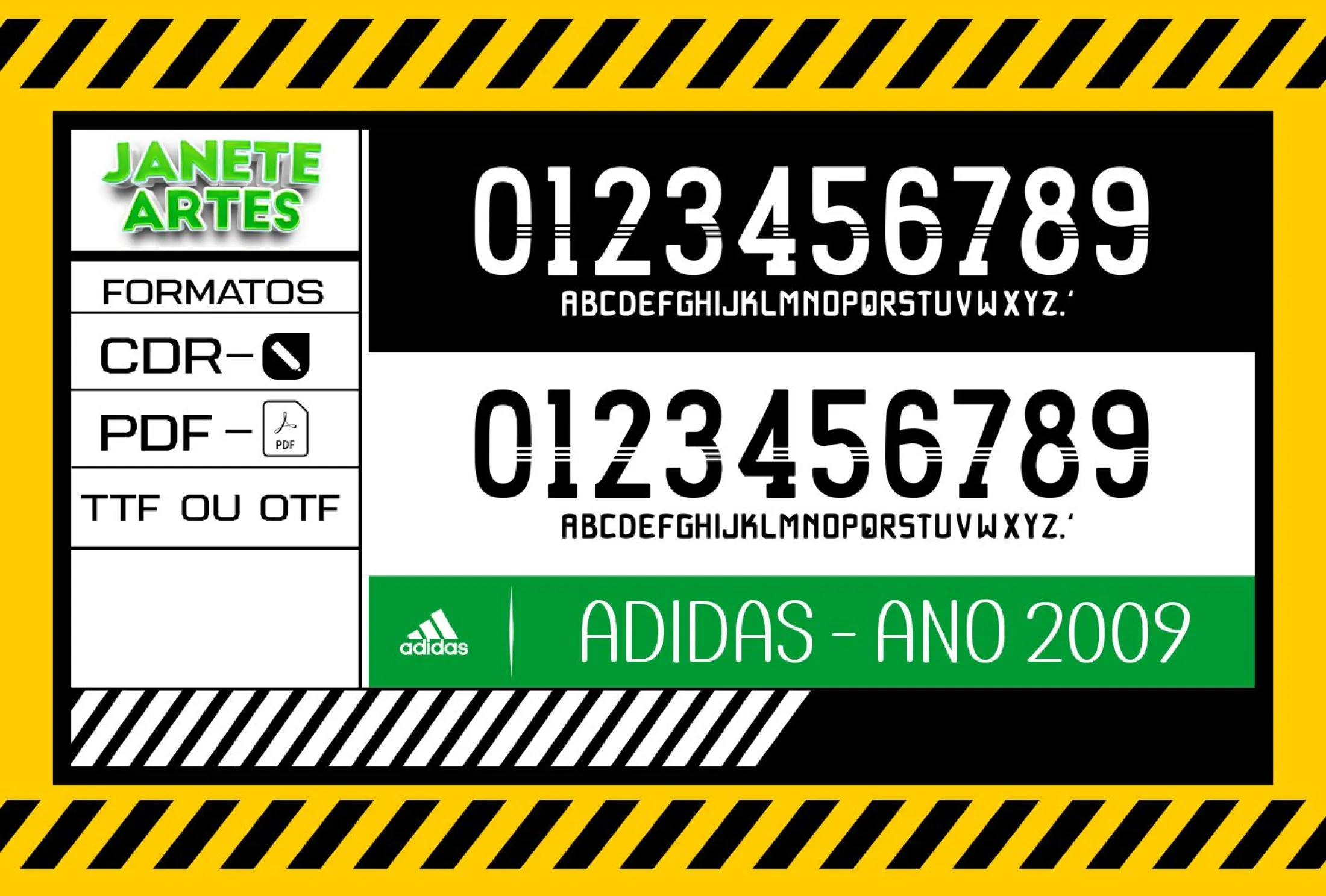
Fonte de Time Tipografia Adidas 2009
Uma história que conecta paixão e design
Imagine a emoção de um torcedor ao ver seu time vencer, vestindo uma camiseta com a clássica Fonte de Time Tipografia Adidas 2009. Foi em um dia de campeonato, na arquibancada, que Lucas decidiu personalizar sua camisa com esse estilo único e retrô. A cada gol do seu time, a camiseta não era só uma peça de roupa, mas um símbolo de orgulho e identificação. Assim nasceu a vontade de levar esse conceito para quem ama personalizar e se destacar.
- Perfeito para personalização de camisetas, camisas e blusas com tema esportivo.